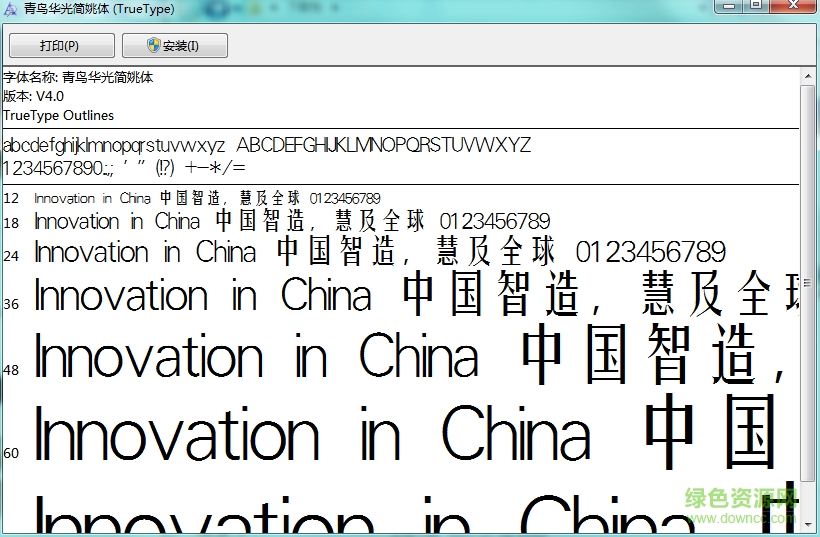
青鸟华光简姚体是一款细线字体,字迹笔直严谨,有着清新的阅读观感和较好的说明作用,如果您喜欢本款字体,那就来绿色资源网免费下载吧!
青鸟华光简姚体是一款字迹清明中和的姚体字体,以细长大方为主,采用宋体欣长娟秀的精髓,让平面设计、名片设计、海报印刷等更显时尚感。
字体隽秀工整,结构狭长,字间距较大,排印清晰,整齐划一,适用于书籍、报刊、杂志的标题字。姚体在宋体的基本骨架上融合了黑体和仿宋体的特点,采取更为简洁概括的笔画形态,整体字型清秀瘦长、端庄正气,呈现出非常鲜明的“美术字”风格。